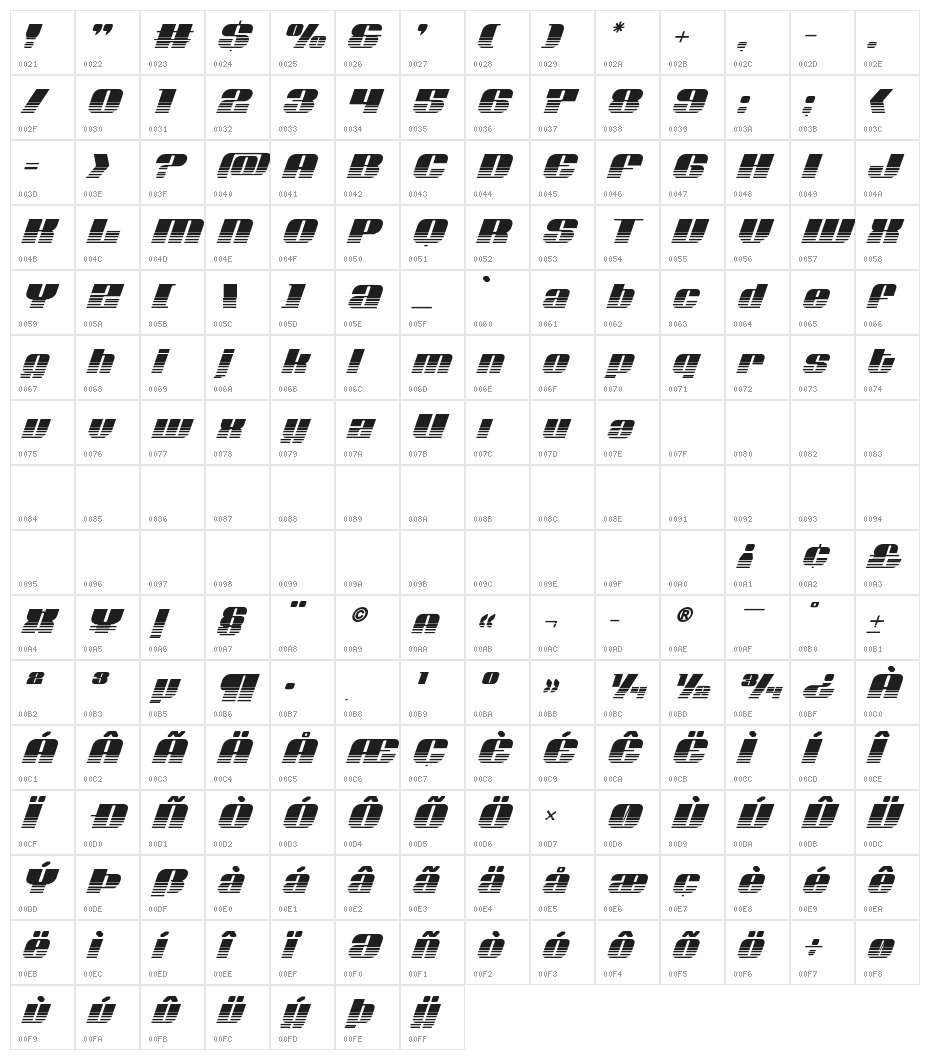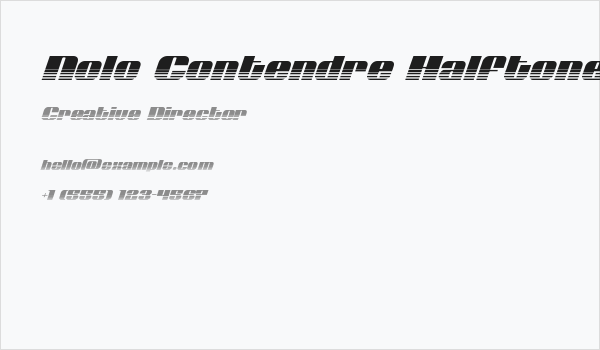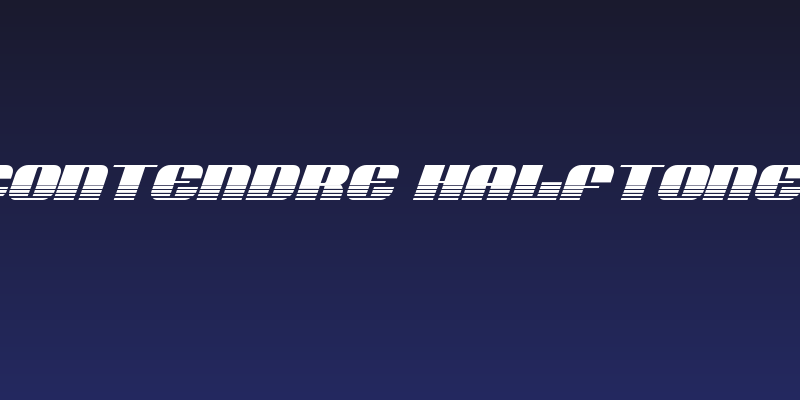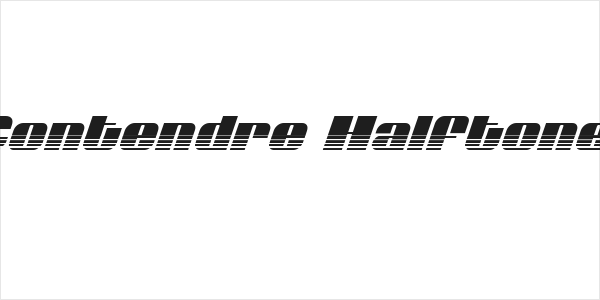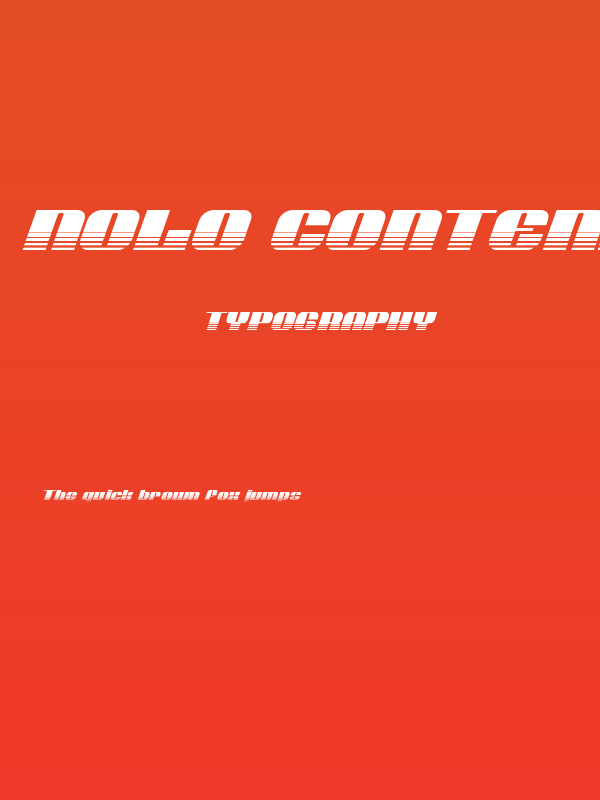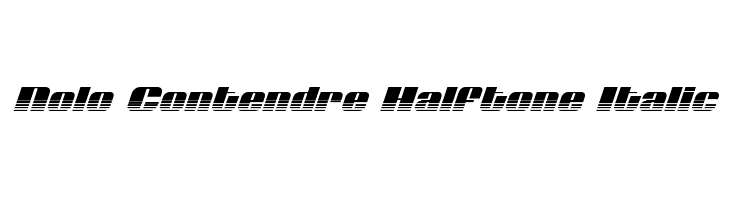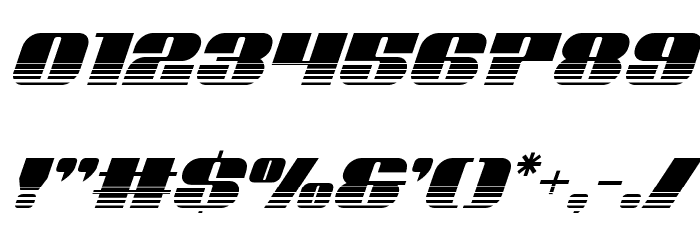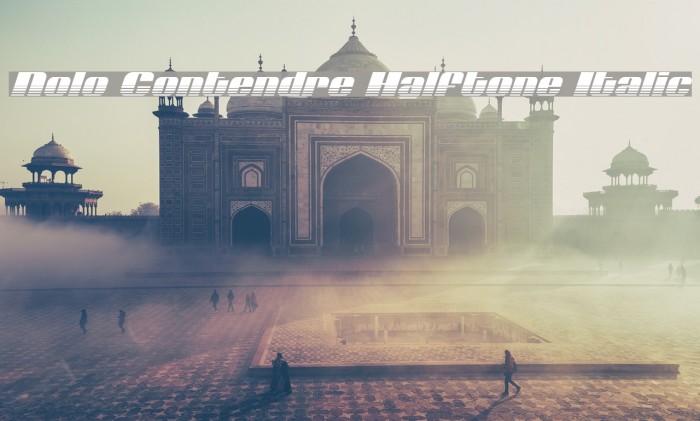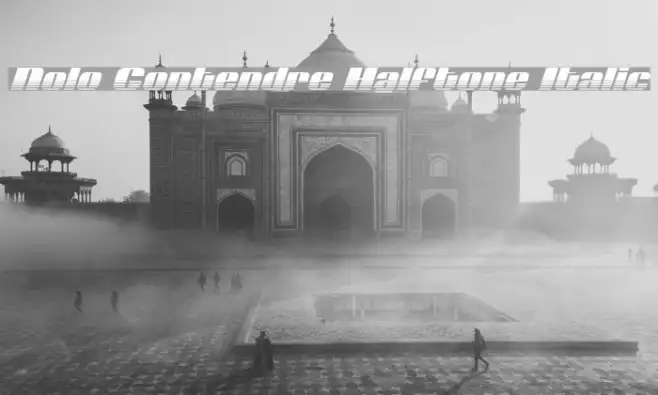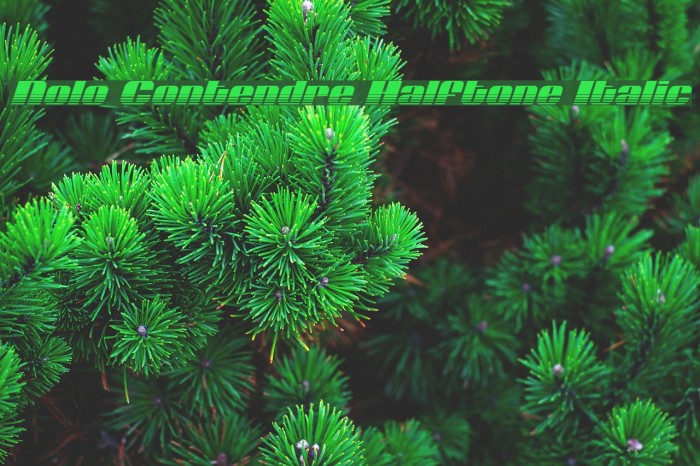
Nolo Contendre Halftone Italic Font
| Proyectos propuestos | Ideal for posters, branding, sports team logos, and any project needing a bold, energetic typeface. |